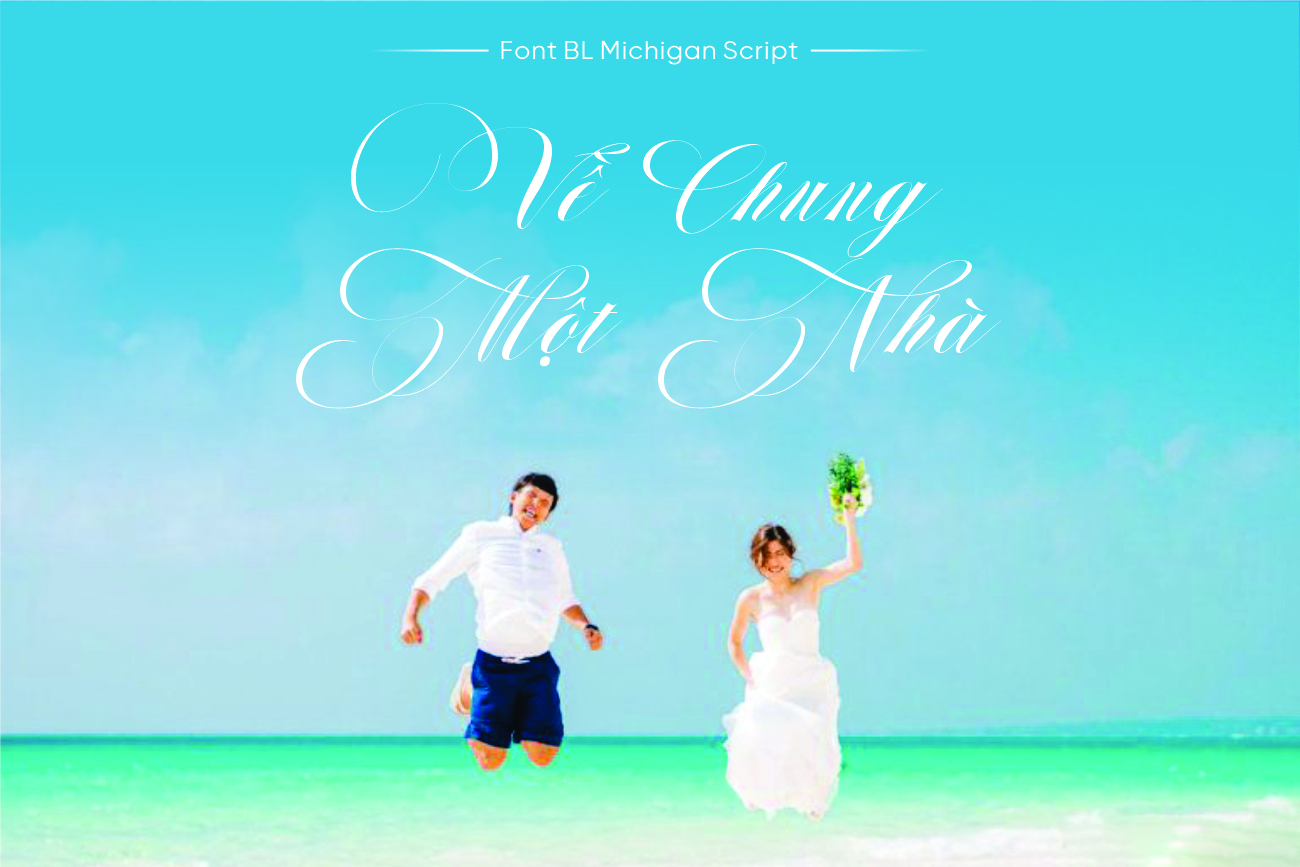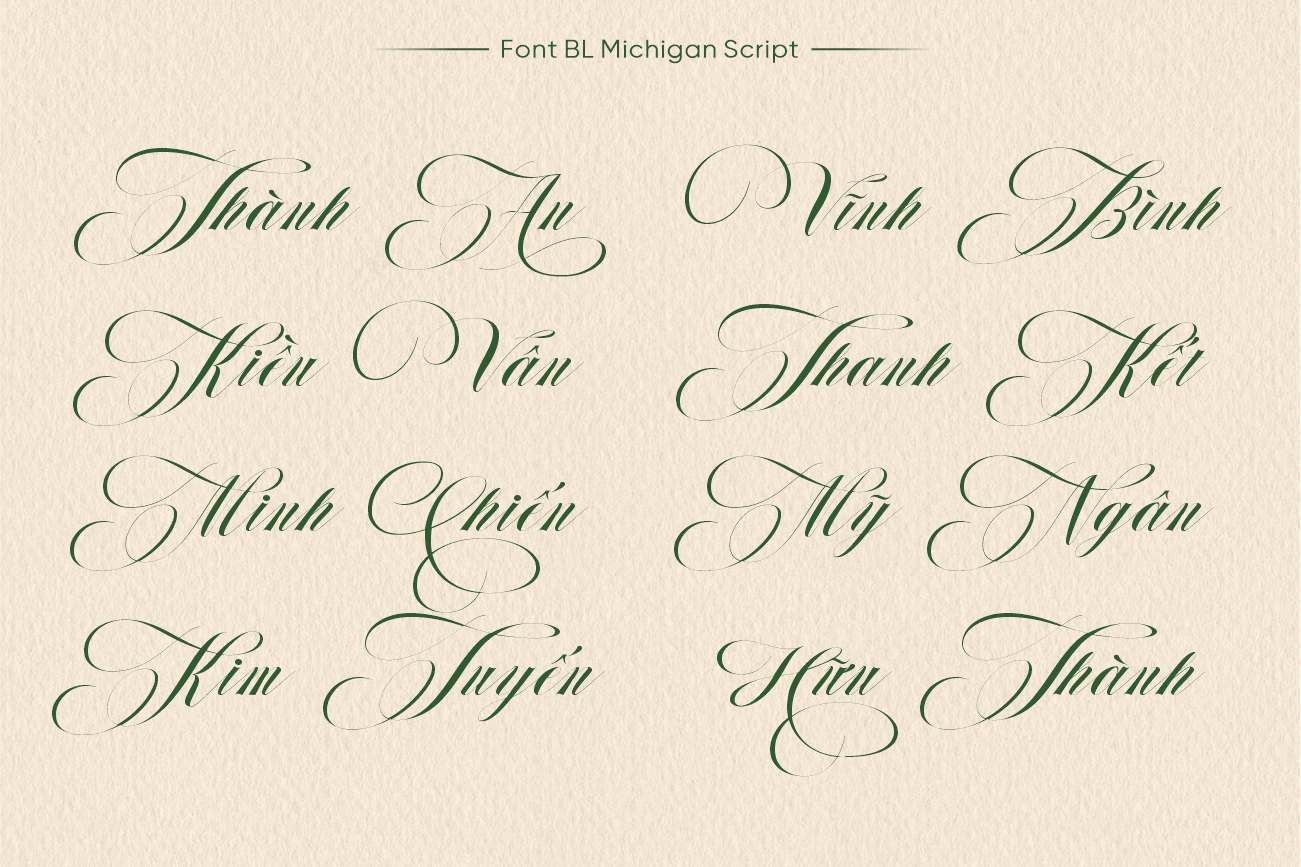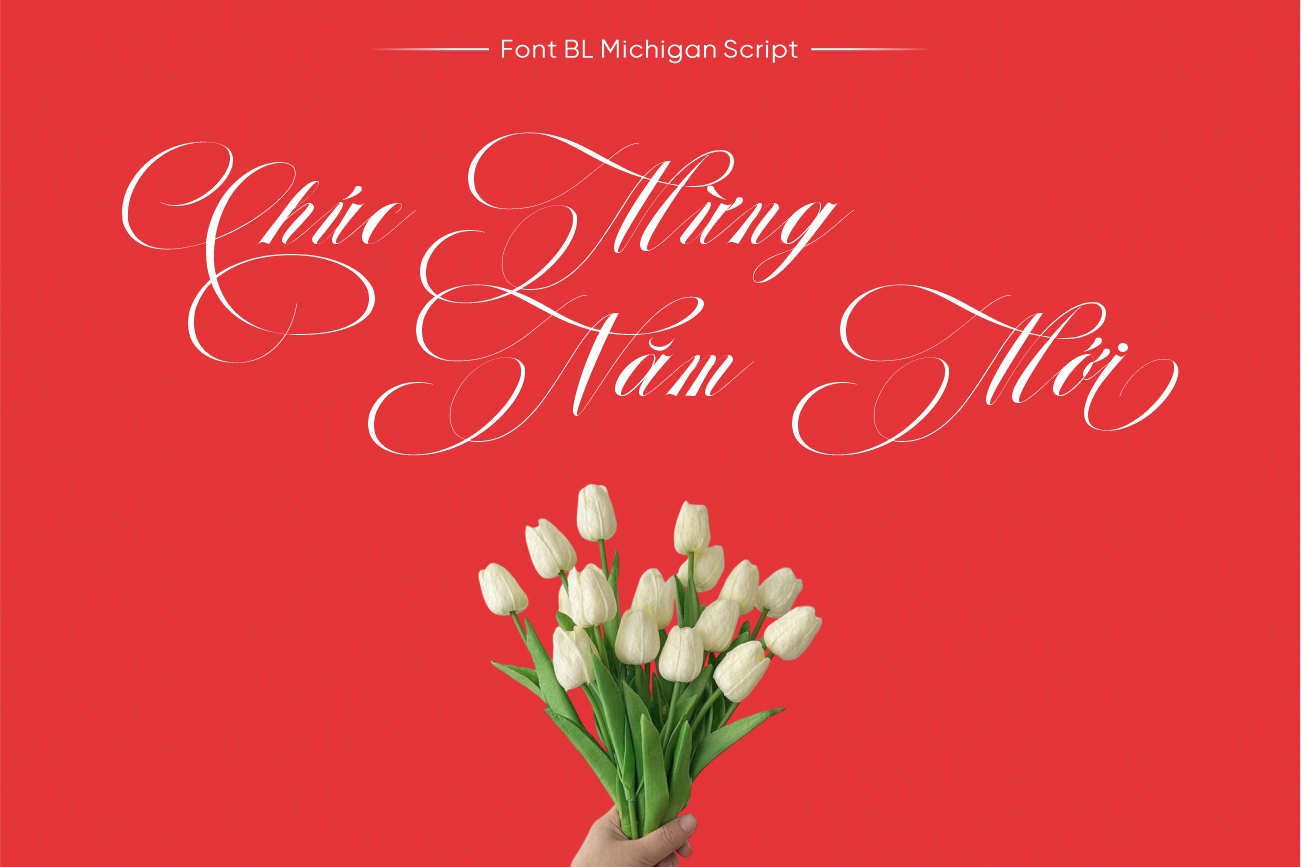
Font chữ Việt hóa sang trọng cho thiệp cưới - BL Michigan Script
Trong thế giới thiết kế sáng tạo, font chữ Việt hóa ngày càng trở thành xu hướng không thể thiếu, đặc biệt trong lĩnh vực in ấn và thiệp cưới. Một trong những lựa chọn nổi bật hiện nay chính là BL Michigan Script – phiên bản Việt hóa từ font Michigan Script gốc, do team BL thực hiện. Font mang đậm phong cách calligraphy tinh tế, bay bổng và cực kỳ phù hợp cho những thiết kế lãng mạn.
Điểm nhấn đầu tiên của BL Michigan Script nằm ở nét mảnh uốn lượn mềm mại, kết hợp hài hòa giữa đường thanh và đường đậm. Sự tinh xảo trong từng ký tự giúp tác phẩm thiết kế trở nên cuốn hút, sang trọng nhưng vẫn giữ được nét gần gũi, dễ đọc. Chính vì vậy, nhiều nhà thiết kế lựa chọn font này khi tạo nên thiệp cưới, thiệp mời sự kiện hay các mẫu typography nghệ thuật.
Khác biệt lớn của BL Michigan Script so với bản gốc nằm ở bộ ký tự tiếng Việt đầy đủ, được Việt hóa cẩn thận để không bị lỗi dấu. Nhờ vậy, font dễ dàng ứng dụng trong môi trường thiết kế trong nước mà vẫn đảm bảo tính thẩm mỹ. Từ các cụm chữ như “Về chung một nhà” cho đến tên cô dâu chú rể, BL Michigan Script luôn thể hiện được vẻ đẹp lãng mạn và tinh tế.
Ngoài thiệp cưới, font còn được ưa chuộng trong thiết kế logo cao cấp, bìa album, thiệp sinh nhật, hoặc bất kỳ sản phẩm nào cần sự bay bổng của nghệ thuật chữ viết tay. BL Michigan Script mang đến sự khác biệt, giúp designer tiết kiệm thời gian nhưng vẫn có tác phẩm độc đáo, ấn tượng.
Nếu bạn đang tìm một font chữ Việt hóa, vừa là font chữ nét mảnh lại vừa là font chữ thiệp cưới sang trọng, thì BL Michigan Script chắc chắn là lựa chọn không thể bỏ qua. Đây không chỉ là một công cụ thiết kế mà còn là nguồn cảm hứng sáng tạo cho mọi ý tưởng nghệ thuật.